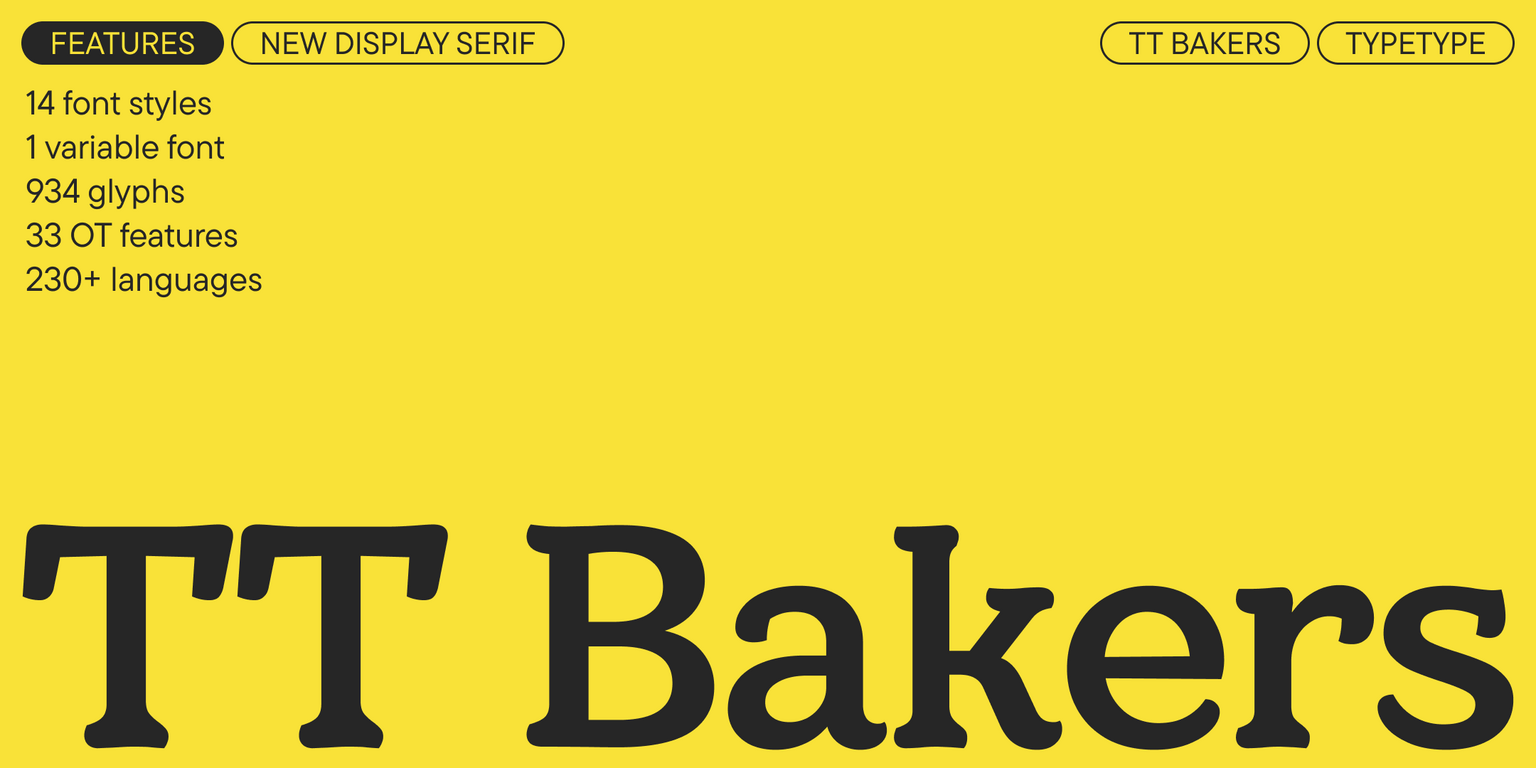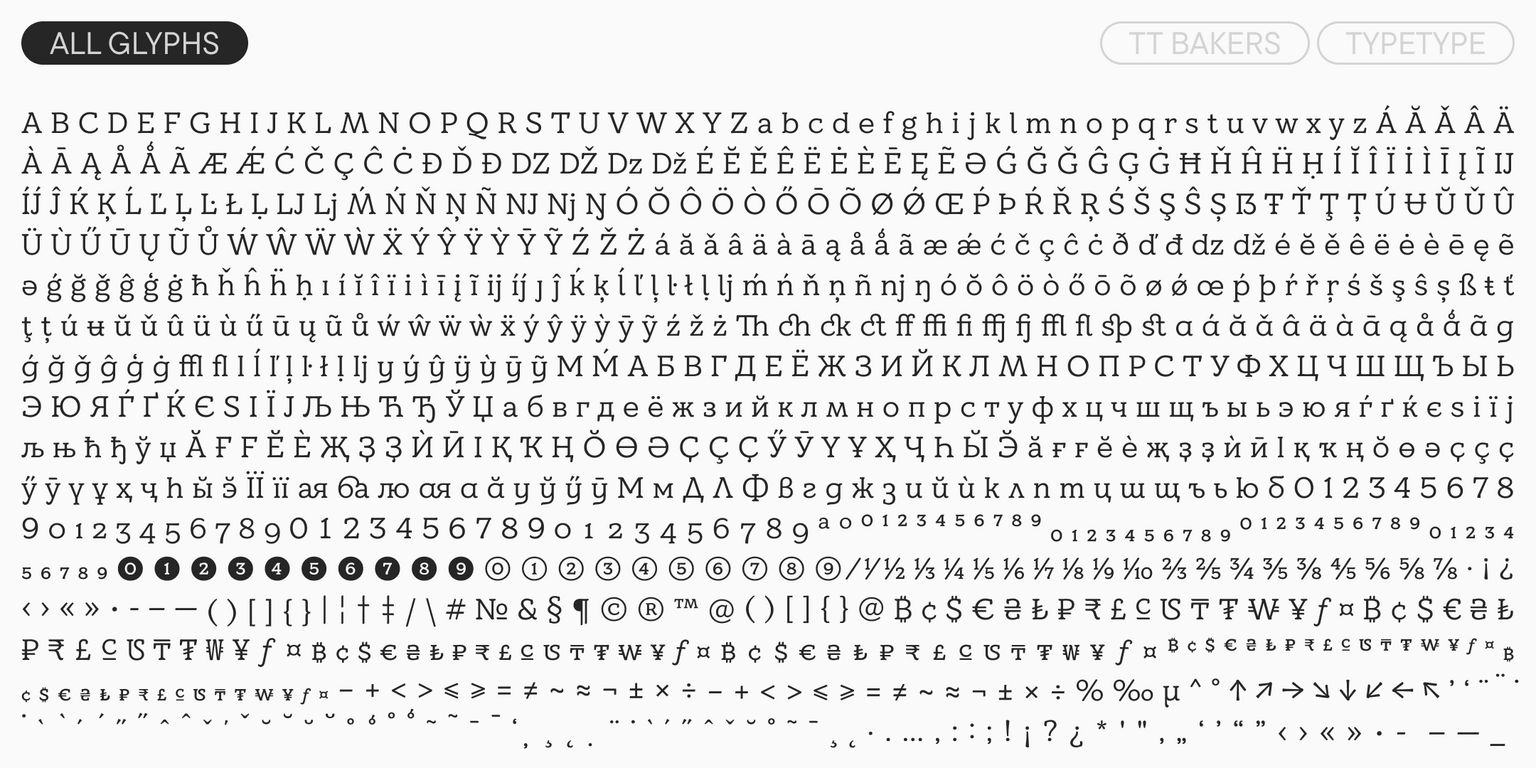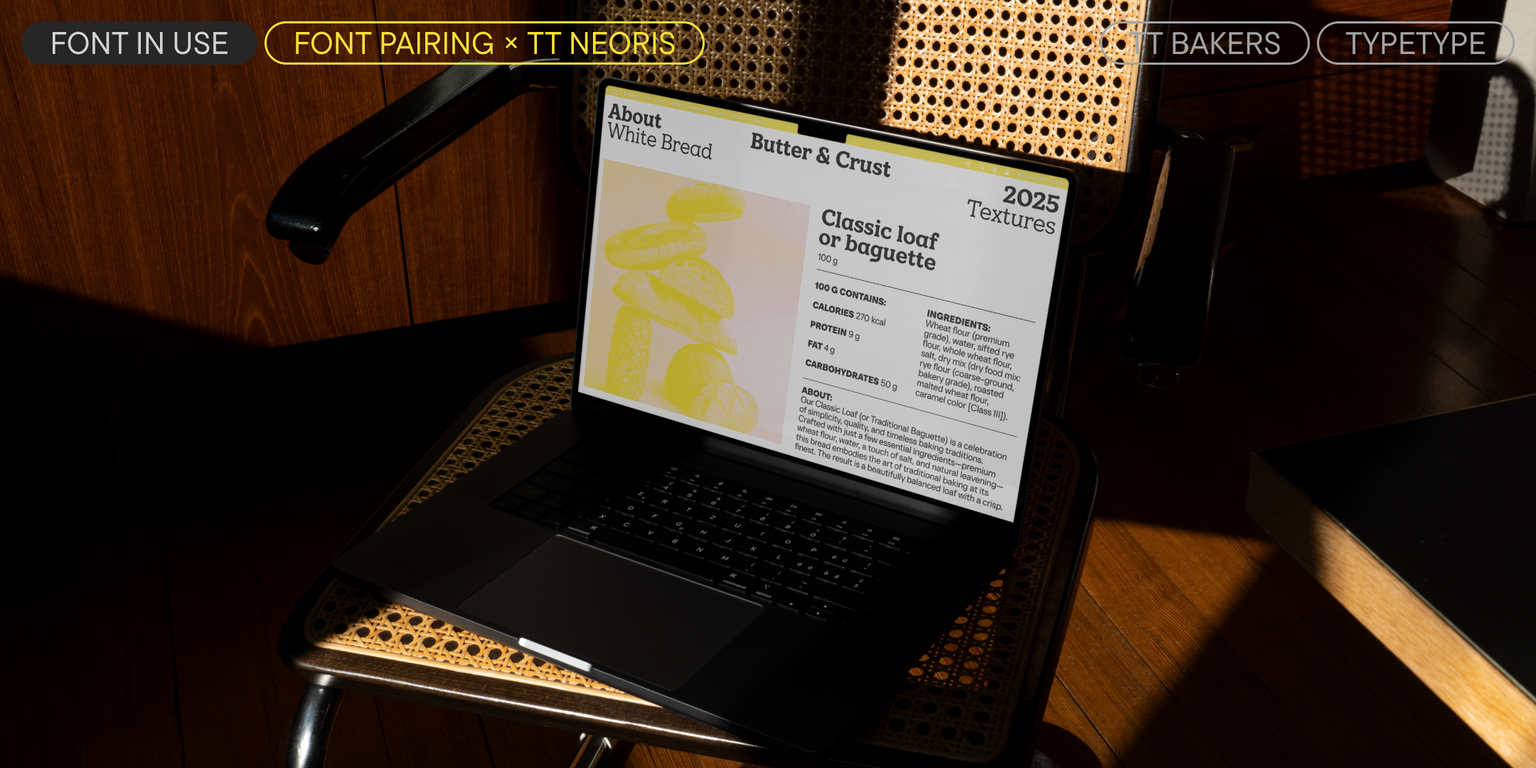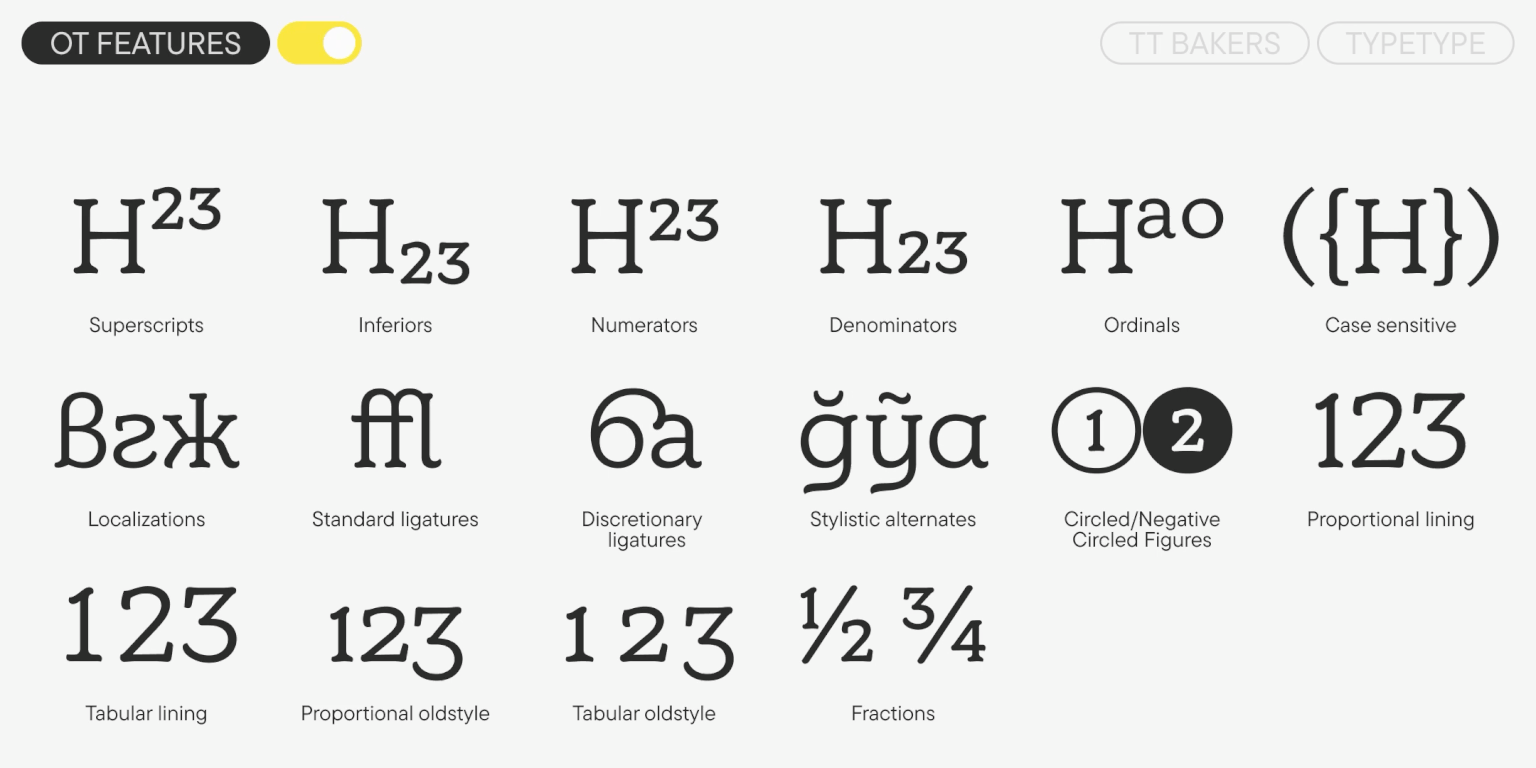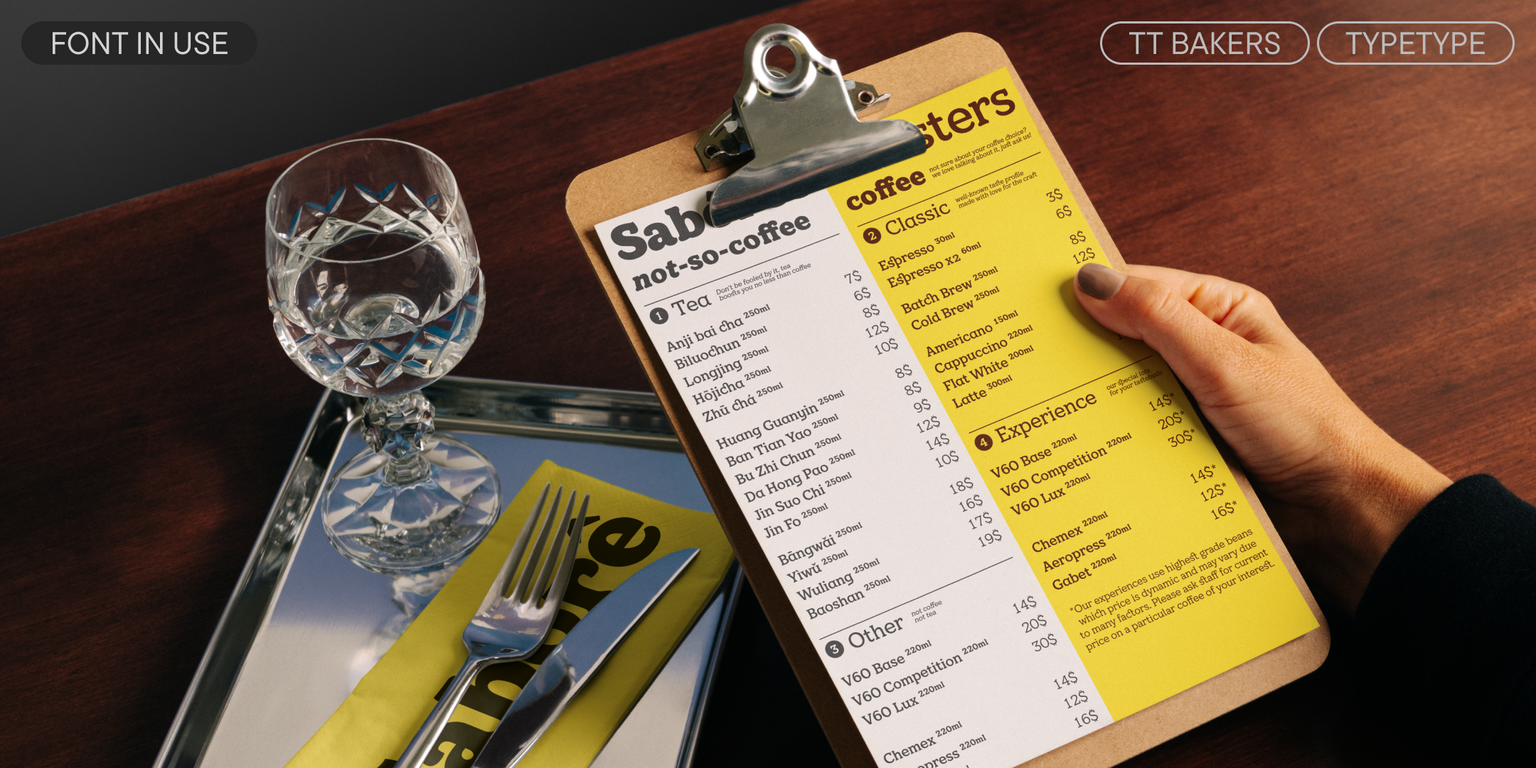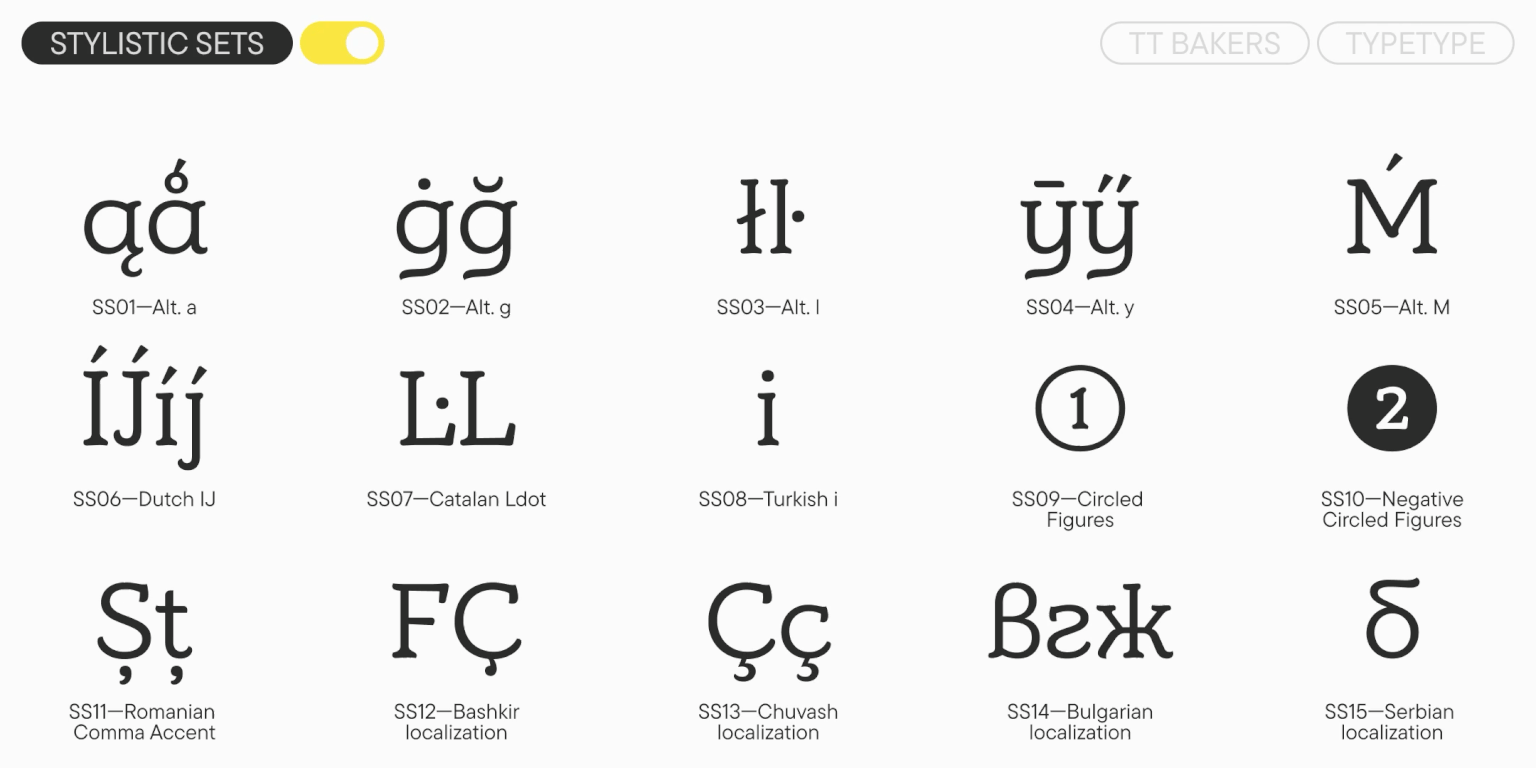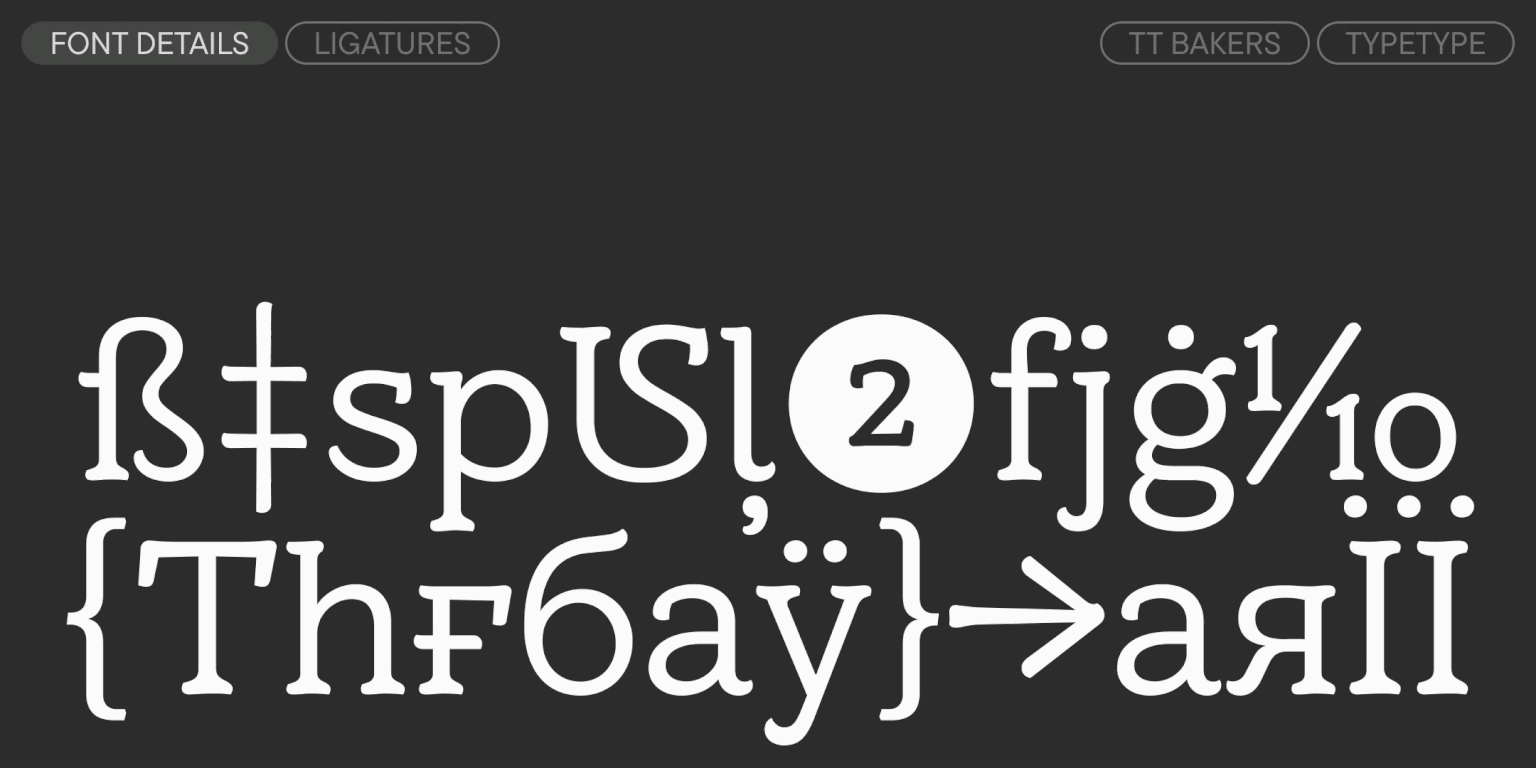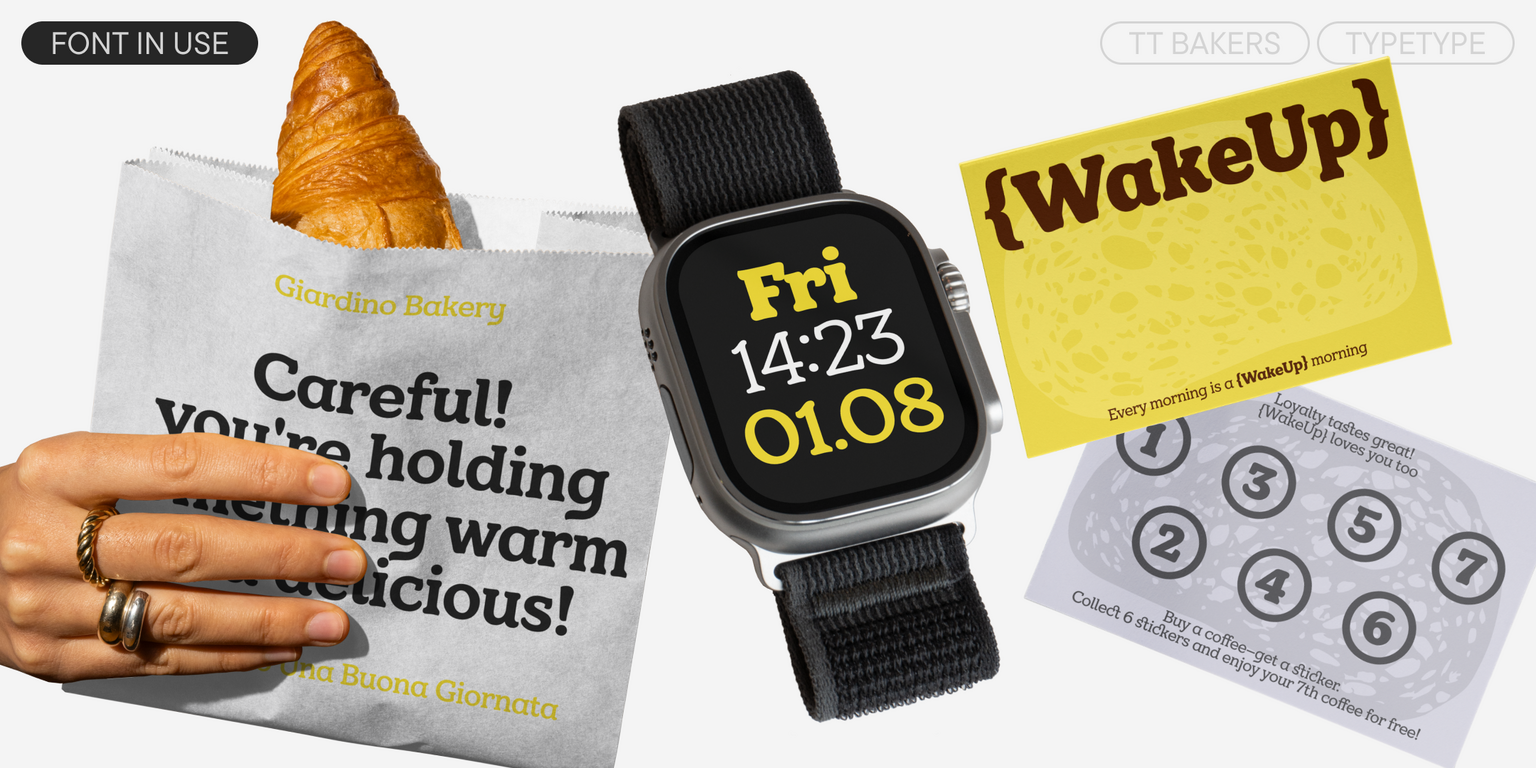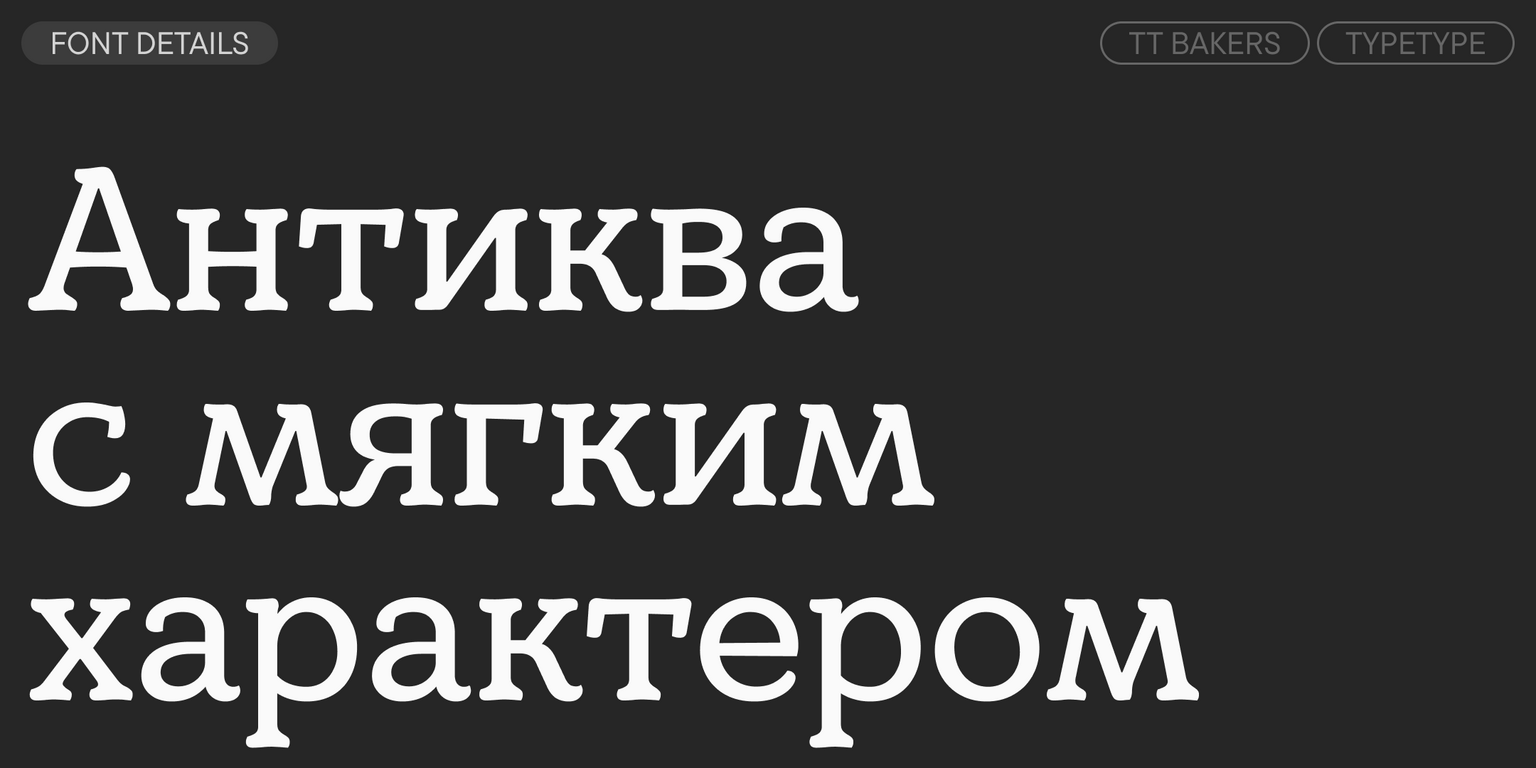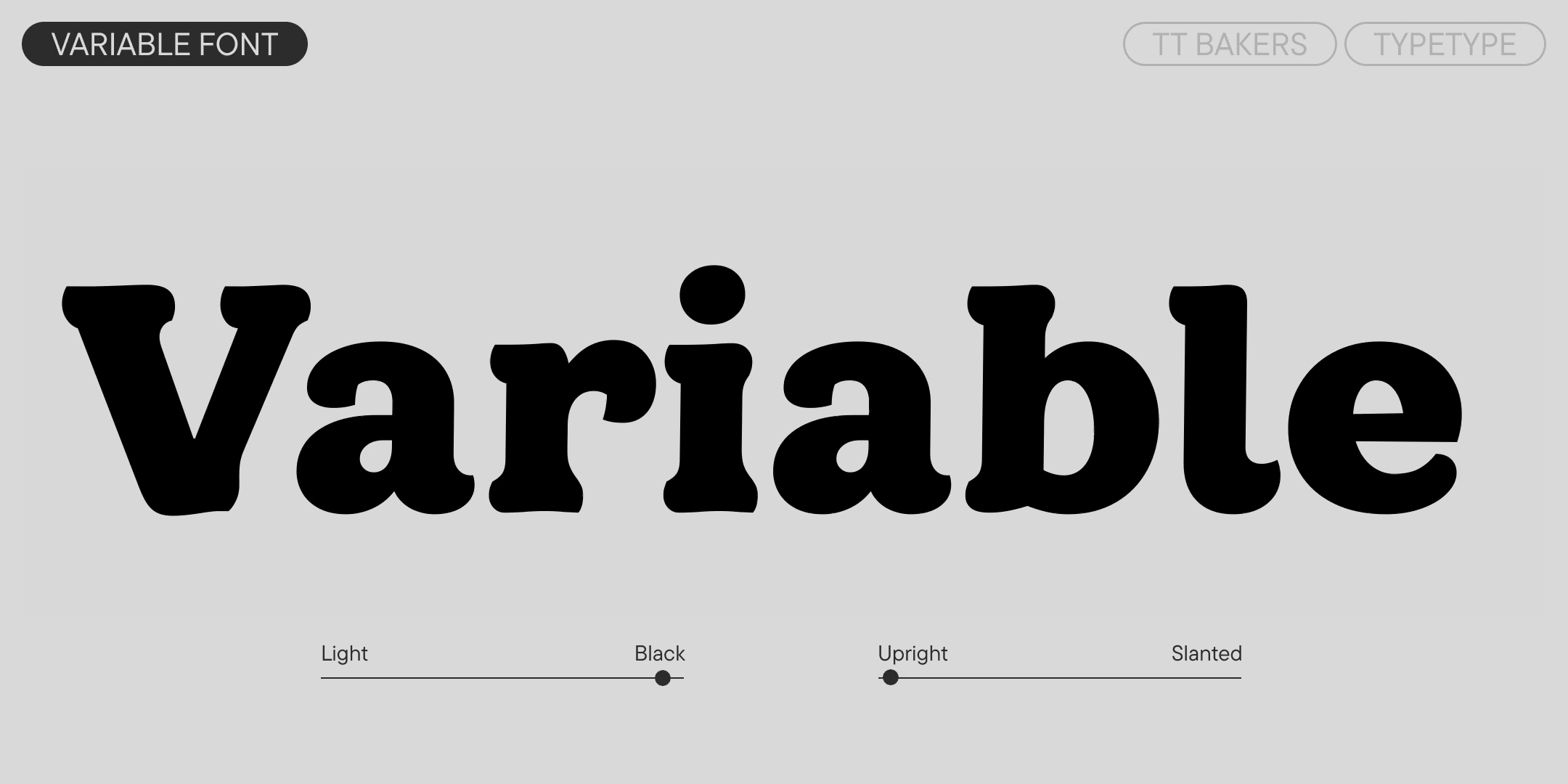
TT Bakers
TT Bakers — ТТ Бэйкерс
Произносится «ТТ Бэйкерс». «Bakers» — производное слово от baker, в переводе с английского «пекарь». Буквы «TT» являются аббревиатурой названия компании.
TT Bakers — пластичная антиква с нежным и живым характером. Этот шрифт похож на свежую выпечку: он тёплый и мягкий, особенно в жирных начертаниях.
TT Bakers
Пластичная акцидентная антиква с мягким характером
TT Bakers
TT Bakers — универсальный шрифт, который одинаково хорошо работает как в текстовом наборе, так и в акциденции. Благодаря сбалансированному контрасту, широкой разрядке и продуманной конструкции TT Bakers сохраняет чёткую читаемость даже в обычном наборном тексте. А в крупных размерах раскрывается его характер: пластичные штрихи, выполненные кистью, придают шрифту выразительность.
TT Bakers
Идеальное решение для проектов, связанных с гастрономией: упаковки хлебобулочных изделий, меню, витрин и фирменного стиля
TT Bakers
Асимметричные засечки создают направленный ритм, украшая чтение
TT Bakers
О гарнитуре TT Bakers
Встречайте новый акцидентный TT Bakers!
TT Bakers — пластичная антиква с мягким и нежным характером. Среди визуальных особенностей этого шрифта — сбалансированный контраст, широкая разрядка и асимметричные засечки, которые создают направленный ритм. Благодаря продуманной конструкции он сохраняет отличную читаемость даже в текстовом наборе. А в крупных и средних размерах проявляется его характер: пластичные штрихи, отсылающие к движению кисти, раскрываются во всей своей выразительности.
TT Bakers станет идеальным решением для проектов, связанных с гастрономией: от оформления упаковки, меню, витрин до создания полноценного фирменного стиля. Нам кажется, что особенно гармонично он будет выглядеть в айдентике пекарен и брендов, производящих хлебобулочные изделия — это мы и отразили в названии гарнитуры. Однако и для проектов с другой тематикой этот шрифт прекрасно подойдёт благодаря своему универсальному характеру.
В TT Bakers входит:
• 15 начертаний: 7 прямых, 7 наклонных и 1 вариативный шрифт, меняющийся по осям жирности и наклона;
• 934 знака в каждом начертании;
• 33 OpenType фичи;
• Поддержка 230+ языков.
TT Bakers — тёплая антиква для мягких акцентов!
ss01 | Alternative a
ss02 | Alternative g
ss03 | Alternative l
ss04 | Alternative y
frac | Fractions
case | Case Sensitive Forms